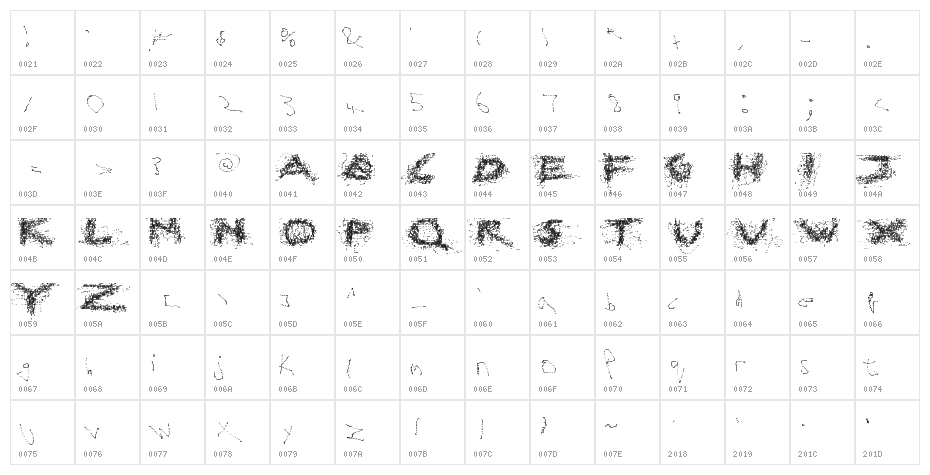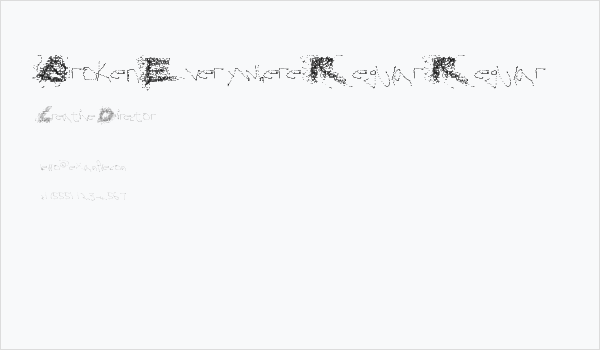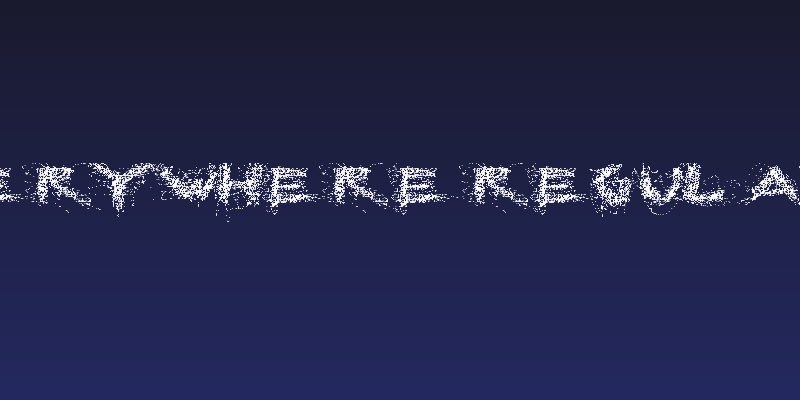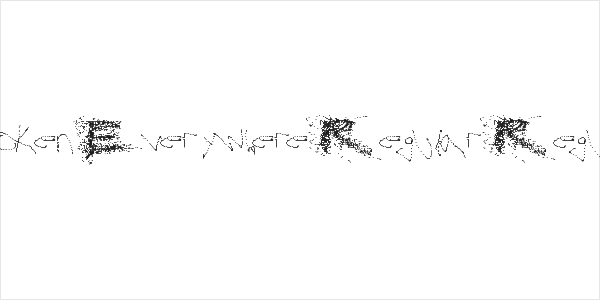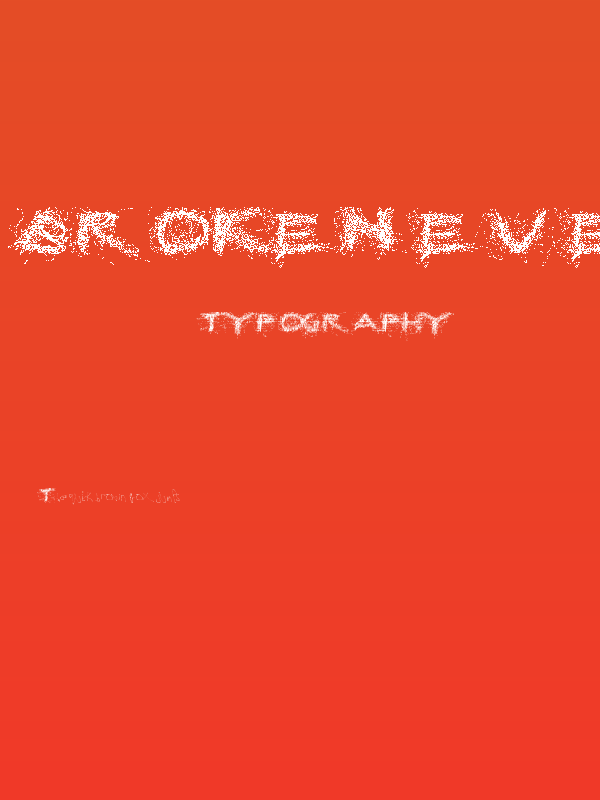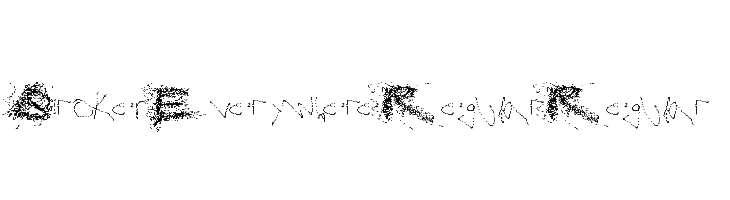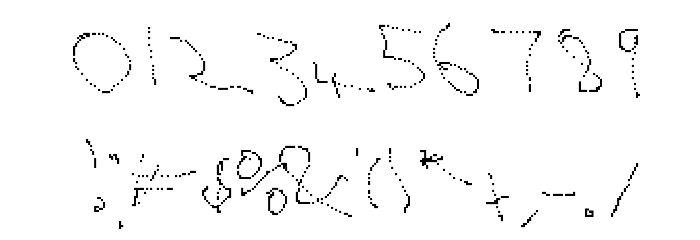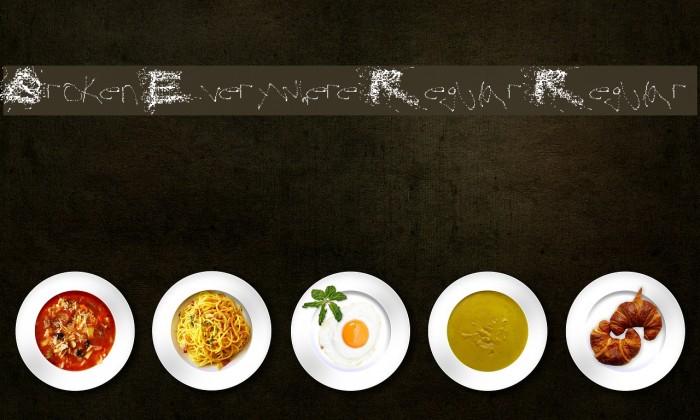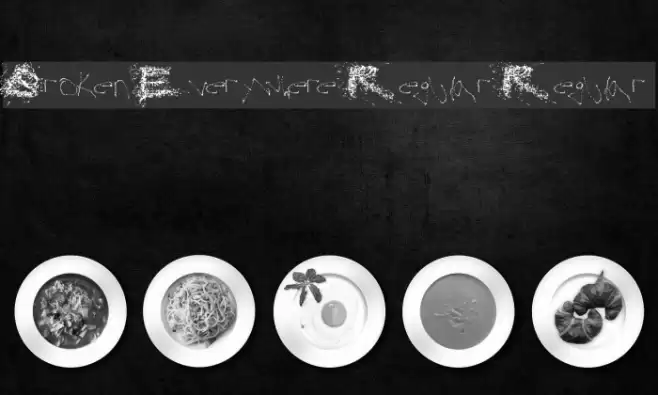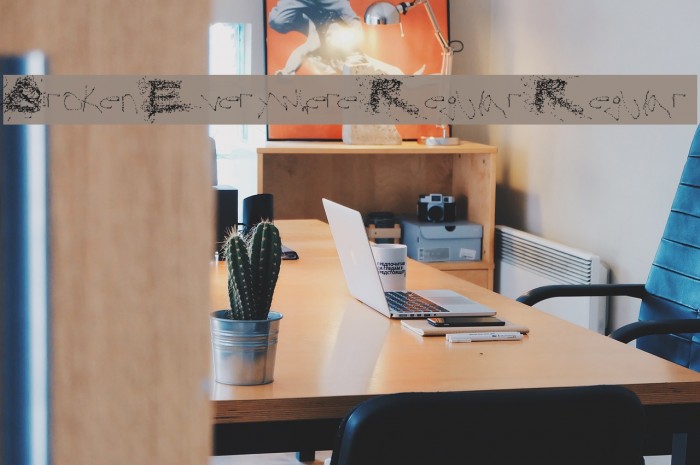
Broken Everywhere Regular Font
✎ Distorted Eroded
| Familia de fuentes | Broken Everywhere Regular |
| Categorías | Distorted Eroded |
| Proyectos propuestos | Ideal for projects that require a grunge or urban theme, such as album covers, posters, and streetwear branding. |